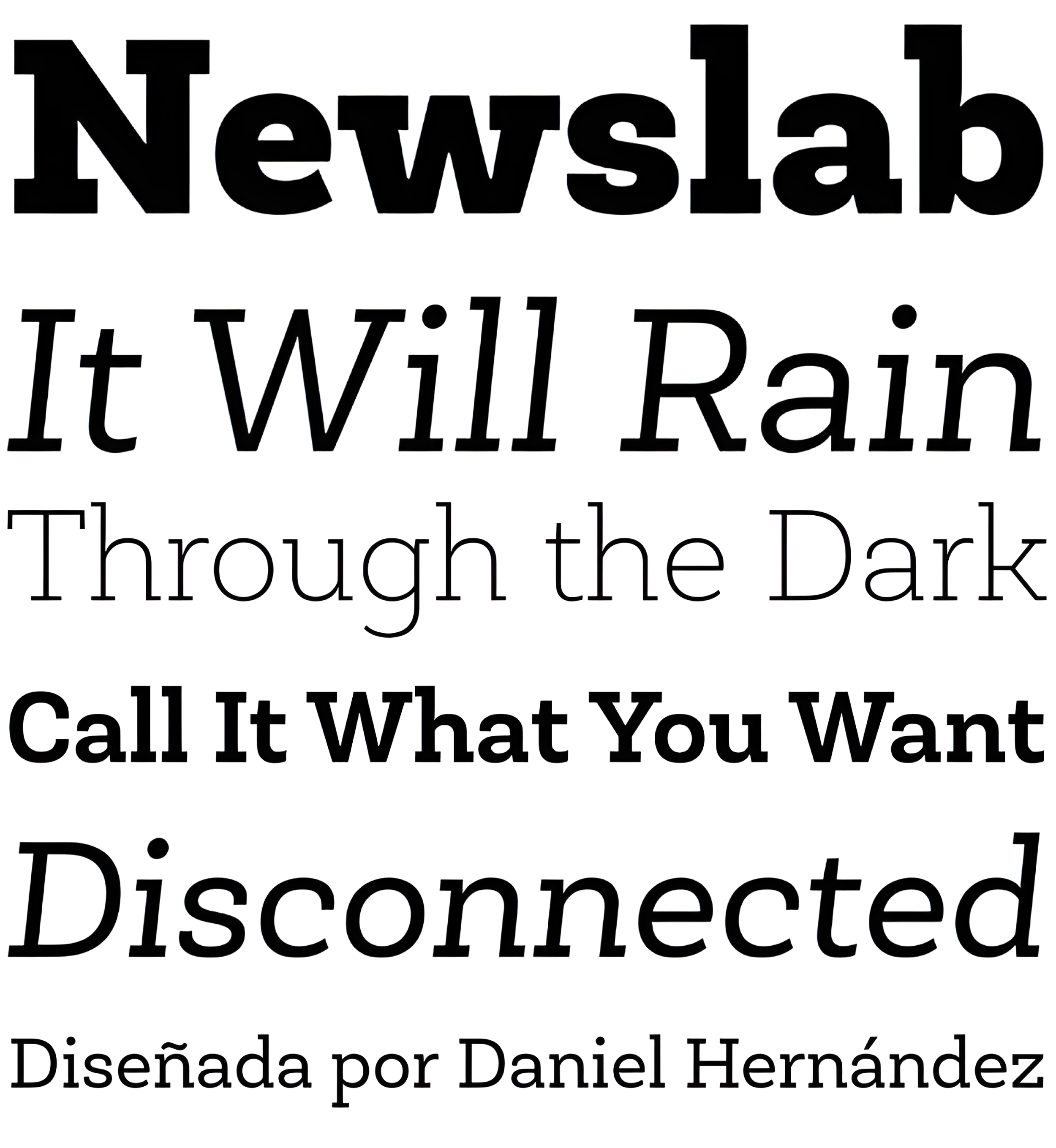
| Descripción | Newslab es una fuente slab serif -diseñada por Daniel Hernández- que es el resultado de la combinación de tres tipos de letra diferentes: Andes, Sánchez y Roble. La armonía entre todas las características de los tipos de letra hace de Newslab una fuente neutra pero imponente. La familia tipográfica Newslab consta de 16 variantes y 8 pesos, con cursiva. Muy adecuada para proyectos editoriales, logotipos, carteles, etc. Las variantes normal y cursiva están disponibles gratuitamente. |
| Familia(s) | Thin, Thin Italic, Light, Light Italic, Book, Book Italic, Regular, Italic, Medium, Medium italic, Bold, Bold Italic, Extra Bold, Extra Bold Italic, Black, Black Italic |
| Estilos | 16 |